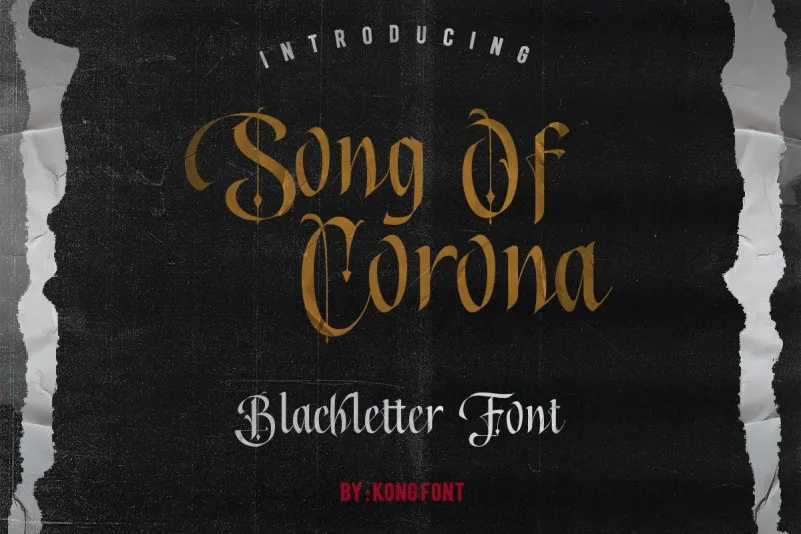
Song of Corona – Blackletter Font – Download Grátis
Aproveite sua visita à página do Song of Corona – uma nova fonte blackletter. Especialmente adequada para projetos criativos, essa fonte é perfeitamente adaptável para criar convites de casamento, aniversários e datas especiais. O nome blackletter refere-se a um tipo de escrita popular em toda a Europa Ocidental entre 1150 e o século XVII. Embora seu visual possa ser considerado tradicional ou gótico, é extremamente leitor e elegante. É uma escolha perfeita para qualquer projeto que busque um toque sofisticado e delicadamente bonito. Para usufruir ainda mais do Song of Corona, essa fonte pertence à categoria de fonts redondas (rounded fonts). Seja você um designer ou um criador de conteúdo online, é uma opção fantástica para tornar seus materiais digitais ainda mais atraentes e agradáveis ao olhar. Foi desenvolvida por f0rdesigner, que nos oferece uma variedade de opções de fontes modernas e vintage. Por ser uma blackletter em forma redonda, o Song of Corona é especialmente adequado para projetos que buscam um equilíbrio entre elegância clássica e modernidade, como branding ou design gráfico. Seja qual seja seu projeto, a fonte Song of Corona está aqui para torná-lo ainda mais bonito.